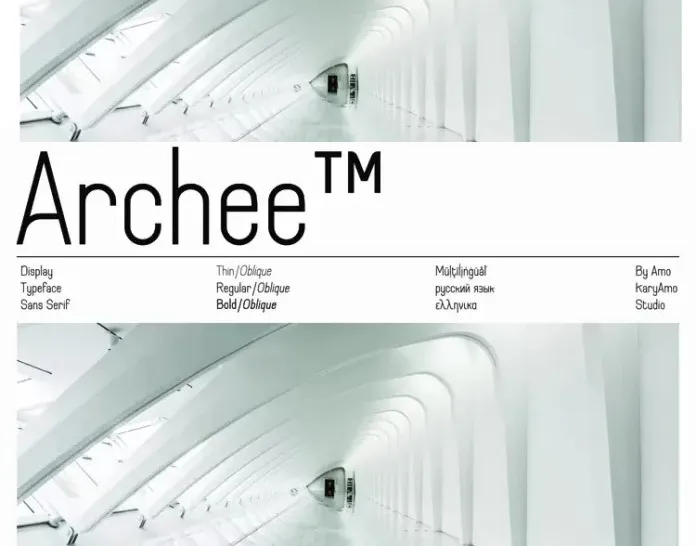
Archee Font – Download Grátis
A Archee Font é uma elegante tipografia sans-serif que se destaca por seus desenhos limpos e leves, sem curvas tradicionais. Inspirada na arquitetura moderna, ela foi projetada para ambientes digitais e textos de tamanho médio a grande. Com formas únicas e um estilo moderno, é perfeita para gráficos que valorizam uma apresentação minimalista e clean. A Archee não só complementará sua identidade visual moderna como também trará uma nova dinâmica ao seu design digital. Seja em redes sociais, websites ou aplicativos de mídia, esta fonte será uma escolha ótima para quem busca um estilo sofisticado e contemporâneo.